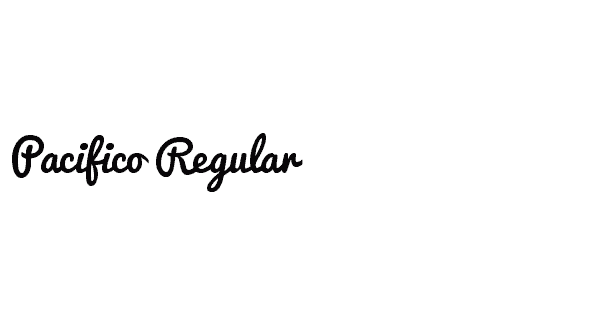
Pacifico шрифт
Pacifico семейство состоит из 2 шрифты
Рукописные
Подражают написанию от руки. Есть множество различных рукописных шрифтов, от каллиграфических до имитирующих быстрое письмо. Воспринимаются они сложно и используются в декоративных целях, например, при написании небольших посланий на поздравительных открытках или как часть логотипа. Популярные рукописные шрифты: Lobster, Nautilus Pompilius, Freestyle Script, Pacifico, Calligraph, TeddyBear, Vivaldy, Veles.
Добавьте свой дизайн
Минимализм и рукописный шрифт обращают на себя внимание
Выберите шрифт, подчеркивающий ваш бренд
Шрифты дополняют друг друга
Ограничить общее количество шрифтов
Используйте не более 2–3 шрифтов в дизайне.
В визитке используется только два шрифта
Если использовать много разных шрифтов, воспринимать информацию становится сложнее
Брендинг
Шрифт визитной карточки должен представлять имидж бренда. Выбор правильного шрифта требует стратегического подхода, творчества и интуиции. Многие компании придерживаются традиционных шрифтов: Arial, Helvetica и Times New Roman. Это хорошие стандартные шрифты, их легко читать, но они вездесущи и не помогут вашему бренду выделиться или отличиться от конкурентов. Вы можете выбрать различные шрифты, которые хорошо читаются, но выделяют ваш бренд. Например, гарнитуры Comic Sans или Franklin Gothic.
Избегайте использования слишком похожих шрифтов
Идея использования нескольких шрифтов в дизайне заключается в создании визуального разнообразия.
Нет смысла выбирать два шрифта, выглядящих одинаково. Лучше сочетать гарнитуры из разных групп: в одном дизайне может быть шрифт с засечками и без, рукописный и без засечек. Также смешивайте начертание: одна надпись с жирным, другая без всего или с курсивом.
При выборе двух шрифтов используйте контраст
Когда вы решите использовать несколько шрифтов, убедитесь, что используемые шрифты имеют существенные контрастные различия. Идеальная комбинация шрифтов должна создавать гармонию. Следуйте простому практическому правилу — найдите два шрифта, которые имеют одну общую черту, но в остальном они сильно различаются. Сочетание засечек с засечками — классический ход.
Ключевым моментом при объединении двух совершенно разных шрифтов является установление четкой иерархии между ними — один шрифт должен быть более заметным. Это может быть достигнуто с помощью подбора размера.
Поддержка русского языка
К сожалению, не все шрифты поддерживают кириллицу, что усложняет их использование.
Если часть текста вашей визитки будет на английском языке, то можете выбрать один шрифт именно для этой части карточки.
Где взять шрифты для визиток
В Мастере Визиток есть все необходимое для создания яркой и запоминающейся визитки. В программе представлены многие современные шрифты, благодаря чему вы с легкостью подберете тот, который наилучшим образом отражает ваш бренд. В программе более 430 шаблонов визиток, разбитых на 20 категорий. Среди них вы найдете подходящую именно вам. Скачайте программу прямо сейчас, чтобы создать для себя и вашей компании визитки, бейджи, клубные и дисконтные карты, подарочные сертификаты и многое другое.
Для Windows 7, 8, 10, XPВам также может быть интересно:
Как напечатать визитки дома
Какую бумагу выбрать для визиток
Как выбрать принтер для печати визиток на дому
Дизайн визиток: краткий ликбез по выбору шрифта для визитки
Сделать такую визитную карточку, которая сможет выделить компанию на фоне конкурентов, — это высший пилотаж дизайнерского мастерства.
Хорошая визитка — та, которая притягивает взгляд. Ее приятно держать в руках и хочется разглядывать. И от выбора шрифта здесь зависит очень многое. В этой статье мы расскажем, какой шрифт для визитной карточки выбрать в зависимости от ее предназначения и существующих в полиграфической отрасли стандартов.
Содержание:
- Визитки со шрифтами без засечек
- Визитки с рукописными шрифтами
- Визитки с винтажными шрифтами
- Визитки со шрифтами с засечками
- Визитки с детскими и “мультяшными” шрифтами
- Почему дизайн визитной карточки так важен?
Визитки со шрифтами без засечек
Все виды печатных шрифтов подразделяются на две категории: с засечками и без засечек. Шрифты без засечек также называются рублеными. К самым известным и легко читаемым рубленым шрифтам относятся Helvetica, Arial, Pragmatica, Tahoma, Verdana и др.
Font: Verdana
Шрифт Helvetica разработал дизайнер из Швейцарии Макс Мидингер в середине XX столетия.
Он представляет собой воплощение таких направлений в дизайне, которые ставили своей целью достижение простоты и чистоты геометрических форм. Шрифт Helvetica стал невероятно популярен. Он является самым известным в мире. McDonalds, Nestle, Energizer, Toyota, Skype, BMW, Intel, Jeep, Lufthansa, Motorola, Olympus, Panasonic, Stimorol, Samsung, Sanyo, Zanussi — во всех этих логотипах используется шрифт Helvetica. Его миссия — нравиться всем.
Arial и Pragmatica – это шрифты, созданные десятилетиями позже “по образу и подобию” шрифта Helvetica другими дизайнерскими бюро. Можно сказать, что все три версии практически идентичны. Любая из них идеально подходит для создания визиток. Если вы приверженец современных и минималистичных дизайнерских решений, шрифт без засечек – это ваш выбор.
Визитки с рукописными шрифтами
Красивый шрифт, который похож на начертание букв “от руки”, выглядит очень эффектно, однако читается не без труда.
Поэтому при создании визитных карточек использование рукописных шрифтов может быть оправдано только тогда, когда они являются частью фирменного стиля или отражением вида деятельности владельца. Это главным образом относится к визиткам людей творческих профессий: поэтов, писателей, музыкантов, художников, скульпторов, актеров и т. п.
В “топ” рукописных шрифтов для визитных карточек входят Lobster, Calligraph, Nautilus Pompilius, Freestyle Script, Veles, Pacifico, Teddy Bear, Vivaldy и пр. Среди них есть и «витиеватые» (замысловатые, осложненные украшениями) и «вензельные» (с большим количеством вензелей и росчерков) шрифты. Обратите на них внимание, если хотите продемонстрировать изящество и роскошь вашего бренда.
Некоторые рукописные шрифты создают полную иллюзию того, что текст выведен рукой человека. Вспомните, как выглядит логотип компании Cadillac. Разве он не похож на стильную роспись миллионера?
Для слов, набранных рукописными буквами, нужен бо́льший размер шрифта.
Контактная информация в таком случае набирается другим шрифтом, который должен просто и легко читаться.
Визитки с винтажными шрифтами
Винтажный стиль отличается особым шармом и очарованием. Конечно, он не подойдет тем бизнесменам, которые в своей деятельности акцентируют внимание на инновациях, современных трендах, новых технологиях и т. д. Зато с его помощью можно подчеркнуть многолетний опыт, традиции, а значит, надежность и стабильность. Если вы захотите создать винтажные визитные карточки, вам придется соблюдать два главных правила – использовать приглушенные, словно выцветшие от времени, цвета и подобрать атмосферный ретро-шрифт. Такой, например, как Campton, Duma, Streetwear, Soria и т. п.
Простой, строгий и достаточно нейтральный Campton идеально подойдет для визитной карточки, владельцу которой нужно произвести впечатление респектабельной основательности. Подобные шрифты широко использовались в 50-60-х годах прошлого столетия, но и в наши дни они не теряют своей актуальности.
Duma и Streetwear – шрифты, которые также отлично подходят для создания визитных карточек в винтажном стиле. Они точно передают эстетику 70-х годов ХХ века.
Шрифт Soria можно смело выбирать для использования на визитках, где обыгрывается тема ретро. Он напоминает шрифты, которые использовались в эпоху арт-нуво.
Визитки со шрифтами с засечками
Именно шрифт с засечками первым стал использоваться в издательском ремесле. Обычно он применяется в книжных, журнальных и других объемных текстах. Его основной признак — наличие небольшого штриха, перпендикулярного основанию и(или) концу буквы или знака. Считается, что шрифт с засечками более удобен для чтения, так как засечки создают горизонтальную линию, по которой “скользит” взгляд читающего человека.
Font: Cambria
Самый известный вариант такого шрифта — Times New Roman. Он был разработан в 1930-х годах специально для газеты Times и применялся ею в течение 40 лет.
Шрифт получил широкое распространение в печатном деле и книгоиздании. Существует большое количество его версий разной степени “жирности” и ширины. Если вам хочется, чтобы ваша визитная карточка вызывала ассоциации с английским стилем, сдержанностью, удобством и практичностью, то Times New Roman — лучший выбор.
Courier – имитирует текст, который получается при печати на механической пишущей машинке. Часто используется в программировании в качестве шрифта по умолчанию. Ассоциируется со свободой и способностью выходить за рамки стандартных решений.
Для создания визитных карточек применяются и другие шрифты — Book Antiqua, Day Roman, Serif, Apple, Sanford, Nouvelle, Cambria и пр. Засечки у разных шрифтов выражены по-разному: у одних более ярко, у других — менее.
Font: Serif
Визитки с детскими и “мультяшными” шрифтами
Детские шрифты — это буквы с забавным (“мультяшным”) начертанием. Они поднимают настроение и напоминают о детстве.
К ним относятся такие популярные шрифты, как DisneyPark, Rurintania, Pudelinka, Kot Leopold, Fairy Tale и др.
Представьте себе визитную карточку банковского управляющего с “веселенькими” шрифтами. Возникнет ли доверие к такому банку у потенциального клиента? Нет. А теперь вообразите визитку с надписью “Веселые детские аттракционы” шрифтом Arial или Times New Roman черным по белому. Не слишком-то весело выглядит, не правда ли?
“Мультяшный” шрифт будет уместен не только на визитке с рекламой товаров и услуг, предназначенных для малышей. Если нести людям радость — это цель вашего бизнеса, почему бы вам не украсить свою визитку шрифтом, который будет смотреться не только стильно, но еще и забавно? Как это сделала, например, компания Twitter. Используемый в ее логотипе игривый шрифт Pico Alphabet, в котором угадывается какая-то анимешная история, был создан японской компанией Maniackers Design.
Как подобрать нужный шрифт визитки?
Шрифт на визитке доджен в первую очередь сочетатся с корпоративной типографикой на логотипе.
Если у вас еще нет лого, введите название своей компании и начните разработку прямо сейчас.
Почему дизайн визитной карточки так важен?
Несмотря на свой маленький размер, визитная карточка – не такая уж простая вещь. Грамотно сделанная визитка — эффективный маркетинговый инструмент. Она работает и презентует ваш бизнес клиентам не хуже, чем листовка, white paper или маркетинг-кит.
Разумеется, сейчас есть масса очень удобных альтернатив и более “продвинутых” альтернатив бумажному носителю контактной информации. Однако в любом случае визитки будут менее затратными в изготовлении и распространении, чем любой другой вид рекламной продукции. Минимальный бюджет, который вам потребуется на их изготовление, при правильном подходе даст отличный результат.
Визитки имеют целый ряд серьезных преимуществ перед наружной и другими видами рекламы, среди которых:
- Скорость обмена информацией. Вручение визитки дает возможность собеседнику узнать о вас и вашей деятельности за несколько секунд.
- Корпоративный этикет. Обмен визитными карточками часто используется при установлении деловых связей.
- Компактность. Визитка легко помещается в кармане, портмоне или специальной визитнице.
- Доступность. Заказать изготовление визиток вы можете в любой типографии по приемлемой цене.
- Долговечность. При желании получатель сможет хранить вашу визитку много лет.
Не следует забывать, что само наличие визитки и ее качество, дизайн и шрифт – это элементы имиджа, который играет не последнюю роль в деловых отношениях.
Узнайте больше о визитных карточках читая наши статьи о том, как создать оригинальный дизайн визитки нажав здесь и как подготовить макет визитки к печати — здесь.
***
Выбирая шрифт для ваших визитных карточек, не перестарайтесь с креативом. Что бы вы ни предпочли — шрифт с засечками или без (а может, и их комбинацию), рукописные, винтажные или “мультяшные” буквы — основной задачей при создании визитки прежде всего должна быть читаемость и разборчивость текста.
Человек, взявший в руки вашу визитку, должен моментально понять, кто вы и какой товар или услугу предлагаете.
Помните, что на визитке не нужно много текста, но на ней обязательно должна быть указана контактная информация – адрес, телефон, сайт, ссылки на группы в социальных сетях. Кроме того, прямо на визитной карточке вы можете написать о том, что у ее предъявителя есть возможность получить скидку или бонус. Это станет дополнительной мотивацией для потенциального покупателя заглянуть в ваш магазин или офис.
Существует неписанное правило: на одной визитке допустимо использование не более двух шрифтов. Один из них используем в слогане, в названии бренда в фирменном стиле или в логотипе. Второй — простой и легко читаемый — в остальном тексте. Перед тем как заказывать визитки, ответьте себе на несколько вопросов: зачем они вам, кому и где вы их будете вручать, как ими потом будут пользоваться. Ответы помогут вам определиться как с текстом и цветовым решением, так и с выбором шрифтов.
Понравилась статья? Поделитесь ею в социальных сетях: нам будет приятно. Есть интересный вопрос? Задавайте, у нас наверняка найдется ответ. Знаете о шрифтах то, чего не знаем мы? Делитесь вашими знаниями.
Редактор блога компании Logaster, контент-маркетолог. Эксперт по веб-маркетингу и брендированию. Умеет писать просто о сложном. По ее статьям можно построить успешный бренд и начать успешное продвижение в интернете.
Красивые шрифты для оформления | FLATONIKA
Предлагаю вашему вниманию подборку шрифтов в количестве десяти штук в кириллице и латинице. Все шрифты бесплатны и доступны для скачивания с Яндекс. Диск, в один клик. Красивые кириллические и латинские шрифты могут быть использованы вами для оформления визиток, буклетов баннеров, документов и много чего еще..
1. Pacifico
(бесплатный шрифт (free font), латиница)
2.
Pacifica(бесплатный шрифт (free font), латиница, кириллица)
3. Rodondo
(бесплатный шрифт (free font), латиница)
4. Pagkrati
(бесплатный шрифт (free font), латиница, греческий)
5. Cassandra
(бесплатный шрифт (free font), латиница, кириллица)
6. Alexandra Script
(бесплатный шрифт (free font), латиница, кириллица)
7. Andantino Script
(бесплатный шрифт (free font), латиница, кириллица)
8. Elzevir
(бесплатный шрифт (free font), кириллица)
9. Bad Script
(бесплатный шрифт (free font), кириллица)
10. Dolphins
(бесплатный шрифт (free font), латиница)
Теги: красивые кириллические шрифты, красивый прописной русский шрифт, написание красивым шрифтом, каллиграфические шрифты бесплатно, написать на фото красивым шрифтом, романтический шрифт
А теперь предлагаю послушать пару песен:
Иван Дорн — не надо стесняться
Иван Дорн — Северное сияние
Жмакайте сюда! 🙂
Если вам понравилась подборка нажмите «мне нравится» и поделитесь с друзьями.
Шрифт рисованный карандашом русский. Русские рукописные шрифты
На днях наша группа столкнулась с серьезнейшей проблемой — за пропуски пар надо сдать рефераты, написанные от руки. За два пропуска — 1 реферат на 15 листов! Да я за весь семестр столько бумаги не измарал, слава яйцам. Поэтому пришлось пойти на хитрости, а именно: найти нормальные (кириллические) и загнать их в Microsoft Word, и распечатать наши рефераты.
Вот эта подборка из 80-ти русских рукописных шрифтов. В архиве вы найдете следующие (и др.) экземпляры:
Сделать свой русский рукописный шрифт
Но, скачав эти шрифты, стало понятно, что никто не поверит, будто мы пишем, как Пушкин, Боярский или Моцарт. Поэтому пришлось сделать рукописный шрифт самим. Но как сделать свой шрифт, как две капли воды похожий на ваш обычный почерк?
Для начала устанавливаем Font Creator 6.
Далее, на чистом листе (в линейку и в клетку не подойдут) пишем все буквы русского (английского, и других при необходимости) алфавита, а также цифры и спец. символы.
Сканируем получившееся творение. Далее режем отсканенную картинку на отдельные буковки и циферки (фотошоп или банально пэйнт подойдет), называем соответственно.
Следующий этап в Font Creator:
— Нажимаем файл — новый (New)
— Даем название своему рукописному шрифту (например Moy_shrift), ставим отметку на Unicode, на Regular и на Don’t include outlines (для чистого бланка силуэтов), короче, все по умолчанию.
— Перед вами появляется панель с силуэтами знаков препинания и английских букв. Вам необходимо вставить в нее Кириллицу. Поступаем следующим образом:
1. Нажимаем в верхней строке Вставка (Insert), выбираем Символ (Characters), ДА.
2. Перед вами появляется таблица символов первого шрифта в вашей базе, Затем листаем страницы таблицы кнопкой Block→.
3. Находим русские буквы.
5. Смотрим индекс первой буквы А (у меня $0410) в поле Выбранный Символ (Selected Character).
6. Смотрим индекс буквы я (у меня $044F)
7. В поле Добавьте эти символы (Add these character…) вводим эти числа (как $0410-$044F).
8. Нажимаем Ok.
9. Ваш шаблон пополнился соответствующими силуэтами Кириллицы.
10. Так же вы по отдельности можете вставить туда интересующие вас знаки (Ё,ё и пр.)
Теперь нажимаем на силуэт буквы которую хотите сотворить правой кнопкой мыши.
Затем выбираете пункт импорт изображения (Import image).
В разделе Import image вы нажимаете на кнопку Загрузить (Load).
В следующем окне вы открываете папку, в которой сохранили написанные буквы и символы.
В окне появится изображение этой буквы, нажимаем на кнопку Generate.
Вот ваша буковка и появилась.
Два раза нажимаем на квадратик с вашей буковкой (квадратик в котором раньше был силуэт этой буквы).
Перед вами открывается разлинеенное окошечко. Не пугайтесь большого количества красных пунктирных полосочек, все они вам пригодятся.
Для удобства разверните окно на весь экран.
Если ваша буква чересчур большая или маленькая, то удаляем уже загруженную, загружаем новую и, не нажимая генерировать, жмем на вкладку Глиф. Тут выбираем подходящий множитель (это уже методом тыка) и жмем «использовать по умолчанию».
Далее разберемся с двумя главными линиями (это в разлинеенном окошке) – левая и правая — они определяют то, как будут соприкасаться буквы вашего рукописного шрифта между собой. Если надо, чтобы буквы соприкасались (как в рукописи), правую линию передвиньте на букву (чтобы она чуть-чуть вылазила за линию).
Самая нижняя линия (Win Descent) – максимальный предел для букв с хвостиком (ц,у,щ,з,р,д). Если необходимо, можно ее опустить:
Вторая снизу линия (Baseline)– линия опоры каждой буквы. Если ваши буквы будут по разному стоять на этой линии, то соответственно и в Ворде у вас все будет плясать.
Третья снизу линия (x-Height) – максимальная высота маленьких букв.
Четвертая (CapHeight) – максимальная высота больших букв, цифр, а также буквы «в», и может быть для кого-то «д» и «б».
И пятая снизу линия – линия края верхней строки. (по-моему =)
Как известно, хорошего много не бывает. Это касается и шрифтов. Красивый сбалансированный шрифт может стать украшением любого проекта. Но поиск подходящего начертания порой может занять очень много времени, особенно, если дизайнеру нужен рукописный шрифт. Такие шрифты отличаются от серифов и сан-серифов тем, что зачастую имитируют почерк дизайнера или его видение того, как должен выглядеть рукописный шрифт. Нельзя сказать, что таких шрифтов мало, напротив, их явный переизбыток.
Но действительно хороших рукописных шрифтов, особенно бесплатных, не так уж много, поэтому дизайнерам приходится прочесывать множество сайтов в поисках настоящего алмаза. FreelanceToday предлагает вашему вниманию 20 бесплатных рукописных шрифтов, которые можно использовать как в личных, так и коммерческих проектах.
Рукописный шрифт King Basil, созданный дизайнером Мисси Мейер, отличается плотными штрихами, но при этом он очень мягкий и немного женственный. Шрифт бесплатный, его можно задействовать в самых разных проектах, как цифровых, так и печатных. King Basil отлично подходит для создания логотипов, им можно набирать заголовки, делать анонсы различных мероприятий.
Создательница Milkshake Лаура Уортнигтон стремилась сделать универсальный, дружественный и удобный для чтения рукописный шрифт. И ей это удалось на 100%. Шрифт получился очень удачным, в меру массивным, но не грубым. Символы гармонично перетекают, все буквы хорошо сочетаются друг с другом. Milkshake получился немного винтажным, глядя на него, почему-то вспоминается логотип Coca-Cola.
Шрифт отлично подойдет для ретро-проектов, его смело можно использовать в рекламе продуктов питания или товаров для детей.
Шрифт Variane разработал арт-директор агентства Work Ins Studio Вой Моч Томи. Этот потрясающий рукописный шрифт напоминается о старом добром классическом дизайне и даже удивительно, насколько удачным он получился – ведь для создателя это дебют. Шрифт плотный, символы несколько вытянуты по вертикали, но смотрится очень легко. Отлично подойдет для заголовков, логотипов, его можно использовать в самых разных проектах, ведь он выглядит очень элегантно.
Созданный дизайнером Джеймсом Эдмондсоном рукописный шрифт Lavanderia выглядит очень романтично. Интересно, что источником вдохновения для разработчика послужила надпись, сделанная на окне прачечной, расположенной в одном из районов Сан-Франциско. Lavanderia отличается изящными штрихами и плавными закруглениями. Если нужен шрифт, который должен хорошо вписываться в легкий элегантный дизайн, то это то, что нужно.
Шрифт имеет три начертания, самое легкое из которых выглядит так, как будто символы были выведены очень тонким пером.
Шрифт Fabfelt был создан французским графическим дизайнером Фабьеном Деспино. «Я стремился создать рукописный шрифт без зернистости, естественный и немного старомодный», — рассказывает создатель. Шрифт действительно отлично подойдет для различных ретро-проектов, но им также можно набирать заголовки и использовать его в сочетании с легкими шрифтами без засечек. Отдельно стоит отметить начертание строчных символов – буквы получились настолько удачно, что этим шрифтом можно набирать достаточно большие массивы текста без потери читаемости.
Рукописный шрифт Debby не отличается особым изяществом, тем не менее, выглядит он очень симпатично. Штрихи неровные, немного резкие, что придают шрифту естественность, кажется, что буквы выведены широкой кистью. Он идеально подходит для плакатов, листовок, свадебных приглашений и тому подобных проектов. Там, где нужно добавить естественности и уйти от излишнего формализма, использование Debby будет хорошим решением.
Очень интересный шрифт Black Jack был создан дизайнером Ронной Пеннер из студии Tipadelic. Шрифт немного колючий, напоминающий о не очень хорошем почерке. Однако прописные буквы выглядят очень хорошо, они легкие и хорошо сбалансированные. Несмотря на то, что данный рукописный шрифт доступен только в одном начертании, в нем насчитывается 177 символов, в том числе символы в верхнем и нижнем регистре и все цифры.
Шрифт Allura отличается тонкими размашистыми штрихами, он в меру стильный и романтичный. Однако буквы получились хорошо разборчивыми, так что данный шрифт можно использовать в самых разных проектах. Он отлично подойдет для оформления свадебных приглашений и других проектов подобного рода. Пользователи, скачавшие этот шрифт, отмечают, что он отлично подходит для татуировок. Довольно странное использование рукописного шрифта, но и такое бывает. Да, шрифт совершенно бесплатный, его можно использовать как в личных, так и коммерческих проектах.
Среди рукописных шрифтов порой попадаются настоящие шедевры и Dancing Script как раз такой случай.
Очень красивый, округлый и тщательно выверенный шрифт. В нем прекрасно все: и штрихи, и наплывы и полуовалы. От него буквально веет романтикой. Данный шрифт задумывался как винтажный, но выглядит он очень современно. Строчные символы немного «прыгают», что придает набранному тексту дружественный и неформальный вид.
Anke, один из лучших рукописных шрифтов с открытым исходным кодом, первоначально был разработан дизайнером Анке Арнольдом. Впоследствии к работе подключились другие разработчики и в шрифт были добавлены международные символы Fontgrube Media Design. Шрифт доступен только в формате True Type. Несмотря на то, что Anke выглядит немного неряшливым, это действительно хороший шрифт, который отлично выглядит, если набрать текст строчными символами.
Для рукописного шрифта очень важна разборчивость, особенно, когда речь идет о дизайне логотипов или наборе заголовков. Шрифт Oleo как раз такой: он достаточно плотный, в нем нет ненужных завитушек, поэтому текст, набранный им, будет хорошо считываться.
Шрифт универсальный – его можно использовать в самых разных проектах. Он подойдет для оформления упаковок, свадебных приглашений, им можно набирать заголовки плакатов и листовок. Oleo отличается массивными штрихами, он плотный и уравновешенный. В настоящее время шрифт доступен в начертаниях Regular и Bold.
Этот красивый и немного легкомысленный шрифт был создан Дитером Стеффманом, который решил из наборщиков переквалифицироваться в дизайнера шрифтов. Данный шрифт распространяется совершенно бесплатно, это часть философии его создателя – шрифты являются частью культурного наследия и поэтому должны быть доступны. Honey, размашистый, немного нервный шрифт. Он отлично будет смотреться в различных неформальных проектах.
Marketing Script – это еще одна работа Дитера Стеффмана, которая показывает универсальность этого дизайнера. Шрифт определенно винтажный, такие широко использовались в 60-70 годах прошлого века. Шрифт отличается текучими, связанными символами, которые хорошо смотрятся на большом расстоянии друг от друга.
Marketing подойдет для ретро-проектов, особенно связанных с автомобильной тематикой.
Этот красивый и разборчивый рукописный шрифт был разработан дизайнером Верноной Адамс. Pacifico шрифт достаточно плотный, однако он не выглядит слишком грубым или массивным. Его можно использовать как в печатных, так и цифровых проектах, так как он находится в коллекции Google Web Fonts.
Немного наивный рукописный шрифт Little Days разработан дизайнерами West Wind Fonts. Данный шрифт не предназначен для серьезного использования, он слишком «детской», однако наверняка найдутся проекты, где данный ширфт сможет найти себе применение.
Созданный в студии Sudtipos рукописный шрифт Aquafina выглядит очень элегантно и привлекательно. Он немного «колючий» и очень динамичный, дизайнеры решили сделать его максимально плотным, сократив расстояние между основными штрихами. Шрифт вытянут по вертикали, что позволяет вместить больше символов в строке. Aquafina отлично подойдет для оформления упаковки товаров, для глянцевых журналов и книжных обложек.
Шрифт Freebooter Script был создан канадским дизайнером Грэхемом Мидом. Это довольно экстравагантный рукописный шрифт со множеством интересных деталей. Штрихи в меру плотные и плавные. Если нужно что-то действительно необычное, то можно обратить свое внимание на шрифт Freebooter.
Этот очень интересный ретро-шрифт был создан дизайнером Джеймсом Эдмондсоном (еще один его шрифт есть в нашем списке) в то время, когда он был студентом Калифорнийского колледжа искусств в Сан-Франциско. Шрифт красивый, сбалансированный, очень разборчивый. Если присмотреться к заглавной букве S, можно заметить отсылку к скрипичному ключу – неплохая задумка дизайнера. Шрифт бесплатный, но только для личного пользования. Для использования в коммерческих проектах придется заплатить $30.
Шрифт 5th Grade Cursive – это один из многих рукописных шрифтов, созданных дизайнером Ли Бэтчелором. Этот причудливый шрифт выглядит чуточку старомодным, но так и задумывалось. Он отличается плотными штрихами и отлично подходит для набора больших массивов текста.
Christopher Hand не самый красивый рукописный шрифт, поэтому его популярность стала неожиданной для его создателя Эла Стингера. Многим понравилось, как выглядят неровные и слегка забавные символы. Шрифт можно использовать в различных неформальных проектах, он смешной и даже чуточку брутальный. Chrisopher Hand можно скачать бесплатно, коммерческое использование нужно обговорить с создателем. Эл Стингер не никогда не планировал делать деньги на этом шрифте, так что разрешение можно получить в обмен на футболку с принтом или бутылку текилы.
На этом все, спасибо за внимание!
Помощь сайту
Понравился сайт? Уроки оказались полезными? Вы можете поддержать проект, просто если скачаете и установите приложение «Фонарик» для Андроид. Приложение написал автор сайта и рассчитывает в дальнейшем публиковать свои приложения. Фонарик управляет светодиодом вспышки фотокамеры телефона, а также включает подсветку экраном на полной яркости.
Преимущества: гибкие настройки.
Вы можете задать в настройках, чтобы фонарик сразу включался при запуске приложения и автоматическое включение таймера при запуске приложения. Настройки позволяют отключить блокировку экрана и блокировку фонарика кнопкой включения телефона. Также вы можете самостоятельно установить время таймера.
Если приложение наберёт популярность, это даст стимул автору на создание новых приложений с учётом пожеланий посетителей сайта.
Заранее благодарен, Дмитрий.
QR-код для установки:
Если Вам понравился материал, скажите свое «спасибо», поделитесь ссылками с друзьями в социальных сетях! Спасибо!
Почерк, как умение рисовать, — своего рода искусство. Часто человек не может понять собственного почерка, например, при быстрой диктовке. Сегодня правильное и понятное письмо отходит на второй план, уступая место электронным документам. Но есть ситуации, когда письменная речь должна быть понятна и разборчива. Как исправить почерк и сделать его красивым, расскажет эта статья.
Примеры
Как добиться красивого почерка
Почерк относится к талантам, ведь он напрямую связан с руками. Красивое письмо — род искусства рисования. Не так давно в школах был специальный предмет, направленный на формирование четкого и красивого почерка. Назывался он каллиграфия.
Сегодня школьников уже не заставляют исписывать страницы с одним крючком, чтобы довести написание до идеала. Программа направлена на освоение навыков письма. При этом красоте и аккуратности почерка отводятся последние роли.
Но если за детьми и формированием их почерка следят родители и учителя, то как взрослому человеку научиться писать понятно и правильно? На случай если взрослый человек желает подправить или изменить почерк, существуют несколько полезных советов.
Выбор пишущего инструмента
Удобный пишущий инструмент — ключ к красивому почерку. Не так важно ручка или карандаш. Важно то, что пишущий инструмент удобно лежит в руке и позволяет пользоваться им, не напрягая руку.
Посадка при письме
Правильная посадка при работе с письмом помогает не ощущать дискомфорта. Спину нужно держать прямо, а лист, на котором пишется текст, следует расположить под удобным для написания углом.
Прописи
Главный совет по улучшению почерка — заново прописать задания в школьных прописях. Они помогут вспомнить о правильном написании соединений между буквами и попрактиковаться в их отработке.
Практика
При выработке стиля почерка важно помнить, что постоянная практика позволит лучше запомнить правильное написание всех буквенных элементов. Важно стараться писать чаще и внимательно следить за выполнением написания. К примеру, если не получается написание отдельного элемента буквы или соединение, стоит выписать его на отдельный лист и прописывать до тех пор, пока не получится удовлетворительный результат.
Неторопливость
Не стоит ожидать, что почерк улучшится через час сидения за прописью. При работе над почерком важно делать работу вдумчиво и не торопясь. Если не нравится получившийся результат, стоит над ним поработать еще и сравнить с тем, что было ранее. Прогресс в работе может наступить как через неделю, так и через несколько месяцев.
Фантазия и шрифты
При работе над написанием стоит подключить фантазию или взять за образец понравившиеся прописные шрифты на компьютере. На специальных сайтах много картинок с прописными буквами. В интернете можно найти изображение с понравившимся шрифтом. Возможно, идея дополнить собственный стиль письма длинными росчерками или изящными завитушками, поможет при работе над красотой и стилем почерка.
Смена пишущего инструмента
После освоения одного инструмента стоит попробовать другие приспособления. Если использовалась шариковая ручка, стоит практиковать маркер или перьевую авторучку. Это важно чтобы выработанный почерк не менялся при использовании разных по своей конфигурации инструментов. Таким образом, можно отрегулировать нажим на бумагу и удобный хват для каждого типа ручки или карандаша.
Написание иностранного алфавита
Освоение прописных иностранных букв помогает при внесении правок в собственный почерк. Начать стоит с азов — английский алфавит, написанный красивым почерком, выглядит в достаточной мере похожим на русский, что помогает при проработке проблемных мест на ассоциативном уровне.
С помощью таких несложных советов можно полностью изменить свой почерк, сделав его каллиграфическим. Однако правильный почерк для школы не всегда подходит для взрослого человека.
Почерк взрослого человека несет в себе отпечаток личности и ее уникальность.
Рукописный шрифт русский от руки. Бесплатные рукописные шрифты для скачивания
Почерк, как умение рисовать, — своего рода искусство. Часто человек не может понять собственного почерка, например, при быстрой диктовке. Сегодня правильное и понятное письмо отходит на второй план, уступая место электронным документам. Но есть ситуации, когда письменная речь должна быть понятна и разборчива. Как исправить почерк и сделать его красивым, расскажет эта статья.
Примеры
Как добиться красивого почерка
Почерк относится к талантам, ведь он напрямую связан с руками. Красивое письмо — род искусства рисования. Не так давно в школах был специальный предмет, направленный на формирование четкого и красивого почерка. Назывался он каллиграфия.
Сегодня школьников уже не заставляют исписывать страницы с одним крючком, чтобы довести написание до идеала. Программа направлена на освоение навыков письма. При этом красоте и аккуратности почерка отводятся последние роли.
Но если за детьми и формированием их почерка следят родители и учителя, то как взрослому человеку научиться писать понятно и правильно? На случай если взрослый человек желает подправить или изменить почерк, существуют несколько полезных советов.
Выбор пишущего инструмента
Удобный пишущий инструмент — ключ к красивому почерку. Не так важно ручка или карандаш. Важно то, что пишущий инструмент удобно лежит в руке и позволяет пользоваться им, не напрягая руку.
Посадка при письме
Правильная посадка при работе с письмом помогает не ощущать дискомфорта. Спину нужно держать прямо, а лист, на котором пишется текст, следует расположить под удобным для написания углом.
Прописи
Главный совет по улучшению почерка — заново прописать задания в школьных прописях. Они помогут вспомнить о правильном написании соединений между буквами и попрактиковаться в их отработке.
Практика
При выработке стиля почерка важно помнить, что постоянная практика позволит лучше запомнить правильное написание всех буквенных элементов. Важно стараться писать чаще и внимательно следить за выполнением написания. К примеру, если не получается написание отдельного элемента буквы или соединение, стоит выписать его на отдельный лист и прописывать до тех пор, пока не получится удовлетворительный результат.
Неторопливость
Не стоит ожидать, что почерк улучшится через час сидения за прописью. При работе над почерком важно делать работу вдумчиво и не торопясь. Если не нравится получившийся результат, стоит над ним поработать еще и сравнить с тем, что было ранее. Прогресс в работе может наступить как через неделю, так и через несколько месяцев.
Фантазия и шрифты
При работе над написанием стоит подключить фантазию или взять за образец понравившиеся прописные шрифты на компьютере. На специальных сайтах много картинок с прописными буквами. В интернете можно найти изображение с понравившимся шрифтом. Возможно, идея дополнить собственный стиль письма длинными росчерками или изящными завитушками, поможет при работе над красотой и стилем почерка.
Смена пишущего инструмента
После освоения одного инструмента стоит попробовать другие приспособления. Если использовалась шариковая ручка, стоит практиковать маркер или перьевую авторучку. Это важно чтобы выработанный почерк не менялся при использовании разных по своей конфигурации инструментов. Таким образом, можно отрегулировать нажим на бумагу и удобный хват для каждого типа ручки или карандаша.
Написание иностранного алфавита
Освоение прописных иностранных букв помогает при внесении правок в собственный почерк. Начать стоит с азов — английский алфавит, написанный красивым почерком, выглядит в достаточной мере похожим на русский, что помогает при проработке проблемных мест на ассоциативном уровне.
С помощью таких несложных советов можно полностью изменить свой почерк, сделав его каллиграфическим. Однако правильный почерк для школы не всегда подходит для взрослого человека.
Почерк взрослого человека несет в себе отпечаток личности и ее уникальность.
Как известно, хорошего много не бывает. Это касается и шрифтов. Красивый сбалансированный шрифт может стать украшением любого проекта. Но поиск подходящего начертания порой может занять очень много времени, особенно, если дизайнеру нужен рукописный шрифт. Такие шрифты отличаются от серифов и сан-серифов тем, что зачастую имитируют почерк дизайнера или его видение того, как должен выглядеть рукописный шрифт. Нельзя сказать, что таких шрифтов мало, напротив, их явный переизбыток. Но действительно хороших рукописных шрифтов, особенно бесплатных, не так уж много, поэтому дизайнерам приходится прочесывать множество сайтов в поисках настоящего алмаза. FreelanceToday предлагает вашему вниманию 20 бесплатных рукописных шрифтов, которые можно использовать как в личных, так и коммерческих проектах.
Рукописный шрифт King Basil, созданный дизайнером Мисси Мейер, отличается плотными штрихами, но при этом он очень мягкий и немного женственный. Шрифт бесплатный, его можно задействовать в самых разных проектах, как цифровых, так и печатных. King Basil отлично подходит для создания логотипов, им можно набирать заголовки, делать анонсы различных мероприятий.
Создательница Milkshake Лаура Уортнигтон стремилась сделать универсальный, дружественный и удобный для чтения рукописный шрифт. И ей это удалось на 100%. Шрифт получился очень удачным, в меру массивным, но не грубым. Символы гармонично перетекают, все буквы хорошо сочетаются друг с другом. Milkshake получился немного винтажным, глядя на него, почему-то вспоминается логотип Coca-Cola. Шрифт отлично подойдет для ретро-проектов, его смело можно использовать в рекламе продуктов питания или товаров для детей.
Шрифт Variane разработал арт-директор агентства Work Ins Studio Вой Моч Томи. Этот потрясающий рукописный шрифт напоминается о старом добром классическом дизайне и даже удивительно, насколько удачным он получился – ведь для создателя это дебют. Шрифт плотный, символы несколько вытянуты по вертикали, но смотрится очень легко. Отлично подойдет для заголовков, логотипов, его можно использовать в самых разных проектах, ведь он выглядит очень элегантно.
Созданный дизайнером Джеймсом Эдмондсоном рукописный шрифт Lavanderia выглядит очень романтично. Интересно, что источником вдохновения для разработчика послужила надпись, сделанная на окне прачечной, расположенной в одном из районов Сан-Франциско. Lavanderia отличается изящными штрихами и плавными закруглениями. Если нужен шрифт, который должен хорошо вписываться в легкий элегантный дизайн, то это то, что нужно. Шрифт имеет три начертания, самое легкое из которых выглядит так, как будто символы были выведены очень тонким пером.
Шрифт Fabfelt был создан французским графическим дизайнером Фабьеном Деспино. «Я стремился создать рукописный шрифт без зернистости, естественный и немного старомодный», — рассказывает создатель. Шрифт действительно отлично подойдет для различных ретро-проектов, но им также можно набирать заголовки и использовать его в сочетании с легкими шрифтами без засечек. Отдельно стоит отметить начертание строчных символов – буквы получились настолько удачно, что этим шрифтом можно набирать достаточно большие массивы текста без потери читаемости.
Рукописный шрифт Debby не отличается особым изяществом, тем не менее, выглядит он очень симпатично. Штрихи неровные, немного резкие, что придают шрифту естественность, кажется, что буквы выведены широкой кистью. Он идеально подходит для плакатов, листовок, свадебных приглашений и тому подобных проектов. Там, где нужно добавить естественности и уйти от излишнего формализма, использование Debby будет хорошим решением.
Очень интересный шрифт Black Jack был создан дизайнером Ронной Пеннер из студии Tipadelic. Шрифт немного колючий, напоминающий о не очень хорошем почерке. Однако прописные буквы выглядят очень хорошо, они легкие и хорошо сбалансированные. Несмотря на то, что данный рукописный шрифт доступен только в одном начертании, в нем насчитывается 177 символов, в том числе символы в верхнем и нижнем регистре и все цифры.
Шрифт Allura отличается тонкими размашистыми штрихами, он в меру стильный и романтичный. Однако буквы получились хорошо разборчивыми, так что данный шрифт можно использовать в самых разных проектах. Он отлично подойдет для оформления свадебных приглашений и других проектов подобного рода. Пользователи, скачавшие этот шрифт, отмечают, что он отлично подходит для татуировок. Довольно странное использование рукописного шрифта, но и такое бывает. Да, шрифт совершенно бесплатный, его можно использовать как в личных, так и коммерческих проектах.
Среди рукописных шрифтов порой попадаются настоящие шедевры и Dancing Script как раз такой случай. Очень красивый, округлый и тщательно выверенный шрифт. В нем прекрасно все: и штрихи, и наплывы и полуовалы. От него буквально веет романтикой. Данный шрифт задумывался как винтажный, но выглядит он очень современно. Строчные символы немного «прыгают», что придает набранному тексту дружественный и неформальный вид.
Anke, один из лучших рукописных шрифтов с открытым исходным кодом, первоначально был разработан дизайнером Анке Арнольдом. Впоследствии к работе подключились другие разработчики и в шрифт были добавлены международные символы Fontgrube Media Design. Шрифт доступен только в формате True Type. Несмотря на то, что Anke выглядит немного неряшливым, это действительно хороший шрифт, который отлично выглядит, если набрать текст строчными символами.
Для рукописного шрифта очень важна разборчивость, особенно, когда речь идет о дизайне логотипов или наборе заголовков. Шрифт Oleo как раз такой: он достаточно плотный, в нем нет ненужных завитушек, поэтому текст, набранный им, будет хорошо считываться. Шрифт универсальный – его можно использовать в самых разных проектах. Он подойдет для оформления упаковок, свадебных приглашений, им можно набирать заголовки плакатов и листовок. Oleo отличается массивными штрихами, он плотный и уравновешенный. В настоящее время шрифт доступен в начертаниях Regular и Bold.
Этот красивый и немного легкомысленный шрифт был создан Дитером Стеффманом, который решил из наборщиков переквалифицироваться в дизайнера шрифтов. Данный шрифт распространяется совершенно бесплатно, это часть философии его создателя – шрифты являются частью культурного наследия и поэтому должны быть доступны. Honey, размашистый, немного нервный шрифт. Он отлично будет смотреться в различных неформальных проектах.
Marketing Script – это еще одна работа Дитера Стеффмана, которая показывает универсальность этого дизайнера. Шрифт определенно винтажный, такие широко использовались в 60-70 годах прошлого века. Шрифт отличается текучими, связанными символами, которые хорошо смотрятся на большом расстоянии друг от друга. Marketing подойдет для ретро-проектов, особенно связанных с автомобильной тематикой.
Этот красивый и разборчивый рукописный шрифт был разработан дизайнером Верноной Адамс. Pacifico шрифт достаточно плотный, однако он не выглядит слишком грубым или массивным. Его можно использовать как в печатных, так и цифровых проектах, так как он находится в коллекции Google Web Fonts.
Немного наивный рукописный шрифт Little Days разработан дизайнерами West Wind Fonts. Данный шрифт не предназначен для серьезного использования, он слишком «детской», однако наверняка найдутся проекты, где данный ширфт сможет найти себе применение.
Созданный в студии Sudtipos рукописный шрифт Aquafina выглядит очень элегантно и привлекательно. Он немного «колючий» и очень динамичный, дизайнеры решили сделать его максимально плотным, сократив расстояние между основными штрихами. Шрифт вытянут по вертикали, что позволяет вместить больше символов в строке. Aquafina отлично подойдет для оформления упаковки товаров, для глянцевых журналов и книжных обложек.
Шрифт Freebooter Script был создан канадским дизайнером Грэхемом Мидом. Это довольно экстравагантный рукописный шрифт со множеством интересных деталей. Штрихи в меру плотные и плавные. Если нужно что-то действительно необычное, то можно обратить свое внимание на шрифт Freebooter.
Этот очень интересный ретро-шрифт был создан дизайнером Джеймсом Эдмондсоном (еще один его шрифт есть в нашем списке) в то время, когда он был студентом Калифорнийского колледжа искусств в Сан-Франциско. Шрифт красивый, сбалансированный, очень разборчивый. Если присмотреться к заглавной букве S, можно заметить отсылку к скрипичному ключу – неплохая задумка дизайнера. Шрифт бесплатный, но только для личного пользования. Для использования в коммерческих проектах придется заплатить $30.
Шрифт 5th Grade Cursive – это один из многих рукописных шрифтов, созданных дизайнером Ли Бэтчелором. Этот причудливый шрифт выглядит чуточку старомодным, но так и задумывалось. Он отличается плотными штрихами и отлично подходит для набора больших массивов текста.
Christopher Hand не самый красивый рукописный шрифт, поэтому его популярность стала неожиданной для его создателя Эла Стингера. Многим понравилось, как выглядят неровные и слегка забавные символы. Шрифт можно использовать в различных неформальных проектах, он смешной и даже чуточку брутальный. Chrisopher Hand можно скачать бесплатно, коммерческое использование нужно обговорить с создателем. Эл Стингер не никогда не планировал делать деньги на этом шрифте, так что разрешение можно получить в обмен на футболку с принтом или бутылку текилы.
На этом все, спасибо за внимание!
Мы собрали 101 рукописный шрифт, который вы можете бесплатно использовать в любом дизайне. Задайте настроение бренда с помощью каллиграфии.
Рукописный шрифт — шрифт, созданный каллиграфом с помощью кисти, пера или специальных ручек. Обычно текст, написанный каллиграфическим шрифтом, выглядит более личным и душевным — как будто вы сами написали его от руки. Используйте его, чтобы вызвать доверие и добиться контакта с аудиторией.
Чтобы вы выбрали шрифт, который расскажет о вашем деле все, мы собрали 101 каллиграфический шрифт со свободной лицензией: их можно использовать и в личных целях, и в коммерческих проектах. Когда найдете тот самый шрифт, — и можете создавать свой фирменный стиль!
Бесплатные рукописные шрифты Русские рукописные шрифты 1. CelestinaЭтот рукописный шрифт кажется бодрым и веселым благодаря разной высоте «скачущих» букв. Читается трудно, поэтому не используйте Celestina на длинных текстах.
Скачать с Fontstorage
2. AleksandraCНа мягкие скругленные буквы приятно смотреть, и именно эта округлость превращает обычный гротеск в очаровательный декоративный шрифт. Попробуйте его, если хотите создать ощущение уюта.
Скачать с Fonts4web
3. Brush font oneВыразительный шрифт с угловатыми буквами. Подойдет, когда нужно создать эффект написанного вручную текста.
Скачать с Nomail
4. AlexanderКлассический каллиграфический шрифт для официальных документов и деловых бумаг.
Скачать с Webfont
5. АркадияАскетичный и сдержанный шрифт. Если бы не аккуратные петли, его сложно было бы отличить от обычного гротеска.
Скачать с Behance
6. ElowenПара из каллиграфических шрифтов толстой кистью. Подойдет для детских или женских брендов.
Скачать с Myfonts
Elowen от Кати Язвинской
7. SlimamifВ одной упаковке — четыре начертания разной толщины (light, regular, medium, bold) и все самые распространенные знаки.
Скачать с Fonts-online
8. Le murmureИзначально шрифт был создан в Париже для фирменного стиля студии Murmure. Позже чешский шрифтовик Алекс Слобженинов адаптировал его к кириллице — и теперь он привлечет внимание к любому молодежному и творческому бренду.
Скачать с Velvetyne
Le murmure от Jérémy Landes, Alex Slobzheninov
9. MolodostКак удалось объединить мотивы из древнерусских рукописных книг и «разложение» цвета в современном мониторе — загадка, но получилось дерзко. Миллениалы оценят.
Скачать с Fex
10. Sprite GraffitiОбъемные буквы этого шрифта хорошо подойдут для блога о хип-хопе или скейтбординге, для принтов на майках и любого другого андеграунда. Йоу:)
Скачать с Fonts-online
11. Serifiqo 4FПетли делают любой шрифт женственнее, а тонкие засечки придают элегантности. Serifiqo подойдет только для заголовков, потому что строчные в нем не отличаются от прописных — читать длинный текст в таком шрифте сложно.
Скачать с Befonts
12. Good Vibes ProСамо название намекает на личный дневник, фотоальбом, приглашение на торжество — все это можно оформить с помощью такого шрифта.
Скачать с Fonts-online
13. Paint-it-BlackНеимоверно красивый альбом из шрифтов с историей. Этот — про древних славян и их таинственную мифологию, но в наборе есть и огонь, и переплетенные корни деревьев — всего 5 кардинально разных шрифтов.
Скачать с Dropbox
14. JelaniМечтательный, легкий и… страшно неразборчивый! Найдите в этом наборе первую букву из названия бренда — и сделайте из нее логотип. Получится что-то загадочное и первобытное.
Скачать с Fontstorage
15. TsarevichПекарни и рестораны национальной кухни, сувенирные магазинчики — этот качественный и продуманный каллиграфический шрифт для вас.
Скачать с Mishapanfilov.ru
16. БерезкиЕще один шрифт Миши Панфилова в нашей подборке. Вытянутые буквы, «нацарапанные» с легкой небрежностью, подойдут неформальному бизнесу — как на вывеске, так и в вебе.
Скачать с Mishapanfilov.ru
17. MADE LikesВ наборе сразу два шрифта — один с засечками, другой рукописный. Поэтому искать шрифтовую пару самому не придется.
Скачать с Dafont
18. DenistinaСложный шрифт, который подойдет не всем. Посмотрите, какой разный наклон у букв и как закручена, например, английская s (да, латиница в наборе тоже есть) — если использовать не в меру, то будет выглядеть неаккуратно.
Скачать с Fonts-online
19.TangakНеформальный шрифт для айдентики кафе или бара.
Скачать с Befonts
20. Nickainley
Аккуратный шрифт с длинными буквами и короткими выносными элементами.
Скачать с Bestfonts
21. LeoHandДля каллиграфического шрифта Leo очень читабельный: им можно набирать цитаты или выноски в вебе.
Скачать с Bestfonts
22. Marck ScriptЕще один каллиграфический шрифт, который удобно читать. Буквы не соединяются в лигатуры, поэтому глаз легко их разделяет и считывает.
Скачать с Fontstorage
23. Balkara CondensedЕще один шрифт, навеянный старинной славянской письменностью. Книжные магазины, музеи, турагентства могут примерить.
Скачать с Dropbox
24. GvozdiГвозди смотрятся шуточно на этой картинке, но автор не врет: если использовать шрифт в образовательных или художественных текстах, например, о войне, читатели заметят эту «злость». Скачать с Fonts-online
25. Kurica LapoiНазвание говорит само за себя: неровный, как бы рваный «Курица лапой» добавит юмора в ваш дизайн. Если не боитесь смеяться над собой, скачайте этот шрифт.
Скачать с Dropbox
26. Lemon Tuesday«Лимонный вторник» можно поставить в заголовке меню летнего кафе — он подчеркнет непринужденность обстановки. Помните, что хотя скачущие буквы выглядят современно, но использовать их слишком часто нельзя: это утомляет читателя.
Скачать с Fontstorage
27. Intro Script Demo MediumОкруглый рукописный шрифт в разных начертаниях: от Light до Black можно использовать в заголовке и подзаголовках, чтобы создать ощущение безопасности и несерьезности. Скачать с Bestfonts
28. VelesКрасивый рукописный шрифт для забавных надписей, может создавать ощущение уюта и простоты.
Скачать с Fontstorage
29. VelesЭто не случайный повтор, а совсем другой шрифт, который обращается к славянской культуре и мифологии. Выглядит настолько современно и эффектно, что можно сделать стильную футболку. Скачать с Dropbox
30. ElfabeНебрежный рукописный шрифт с линиями разной толщины, которые привлекают внимание. Подойдет для вынесенных из текста цитат и небольших блоков текста. Скачать с Ofont
31. TM VinogradШрифт выглядит как набросок в скетчбуке. Для неформальных ситуаций (меню бара, пост в соцсетях, ценник в магазине молодежной одежды) он и подойдет. Скачать с Fontstorage
32. Iriska BrushКаллиграфический шрифт, который имитирует кисть. Хорошо смотрится на однородном фоне, как на открытке внизу. А вот на любом фактурном фоне ажурные буквы потеряются. Скачать с Dropbox
Iriska Brush от Ekaterina Erisova
33. Kobzar KSЕще один «нервный» и «неправильный» шрифт, который имитирует письмо на скорую руку. Подойдет, когда нужно создать ощущение личного общения. Скачать с Fonts-online
34. LletraferidaТолстый основной штрих и жирная капля (кружок на конце букв вроде r, f, a) делают шрифт основательным, а тонкие засечки — аккуратным и приятным глазу.
Скачать с Fontstorage
35. RunaДекоративный шрифт для логотипа, упаковки или обложки музыкального альбома. Длинные заголовки лучше не писать — украшений в этом наборе так много, что текст могут попросту не разобрать.
Скачать с Google Disk
36. MasquerougeВытянутые буквы создают динамику и ощущение современного начертания. А вот украшения, которые отсылают к славянской письменности, создают брутальное настроение. Попробуйте оформить с помощью Masquerouge модные товары для мужчин. Скачать с Dafont
37. kraMkraM хорошо смотрится и на плакатах, и в вебе. Главное — не переборщить.
Скачать с Infogra
kraM от Ксении Семировой
38. MarutyaШрифт тонкий и легкий, но детали вроде черточки над буквой «й» делают его затейливым.
Скачать с Fex
39. Magnolia ScriptПрямые штрихи с изгибами выглядят очень стильно, а аккуратные соединения делают шрифт интересным.
Скачать с Fontstorage
40. SolenaШрифт для альбома путешественника или девичьего дневника.
Скачать с Fontstorage
41. ResphektКрасивый рукописный шрифт, который напоминает письмо тушью. Подойдет скорее для украшения, потому что длинные ряды такого кириллического курсива трудно читать.
Скачать с Fonts-online
Английские рукописные шрифты 42. Аlex BrushКлассический стиль для заголовков. Обратите внимание на короткие выносные элементы — для каллиграфических шрифтов это редкость. Благодаря им с Аlex Brush легче верстать текст, поэтому шрифт очень популярен.
Скачать с
43. Allura RegularЛегкий и аккуратный рукописный шрифт, который подойдет для дизайна упаковки, для печатной рекламы или для сайтов и приложений.
Скачать с .
44. ArizoniaВ этом шрифте чередуются жирные и тонкие линии, и за счет такого контраста на него интересно смотреть. Его можно использовать для фирстиля: он хорошо запоминается благодаря неожиданным декоративным элементам, вроде этого «хвостика» у буквы z.